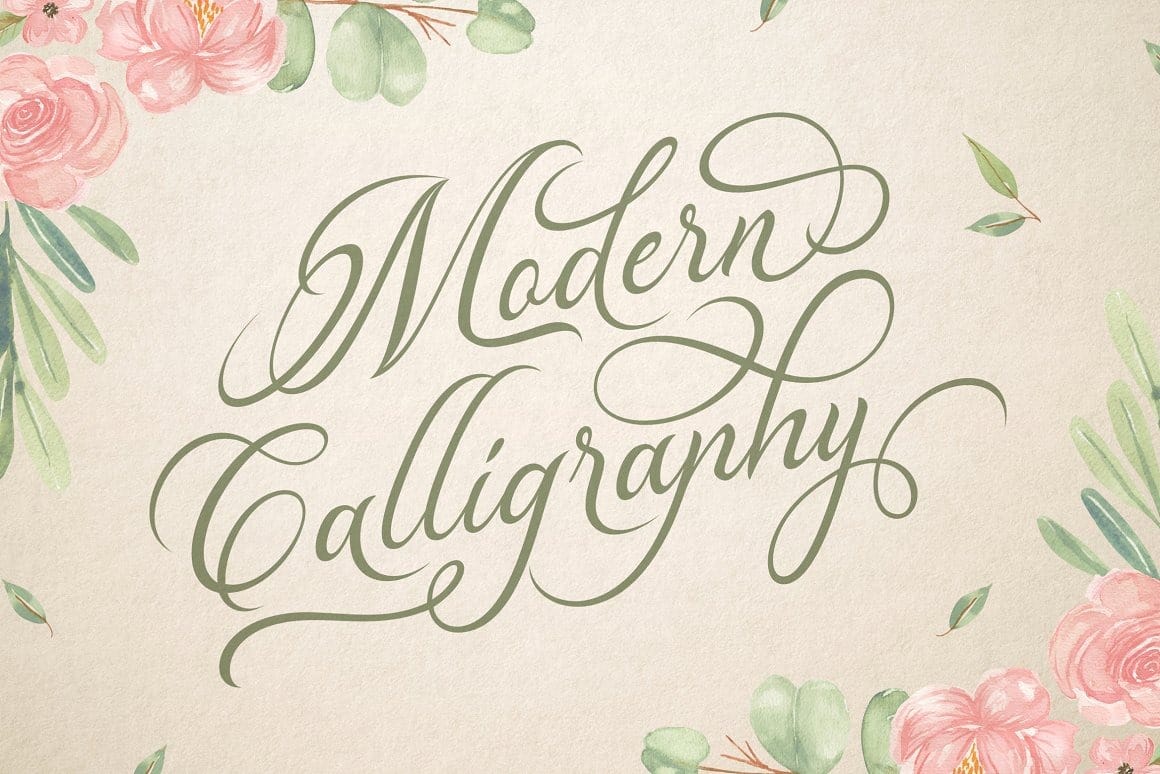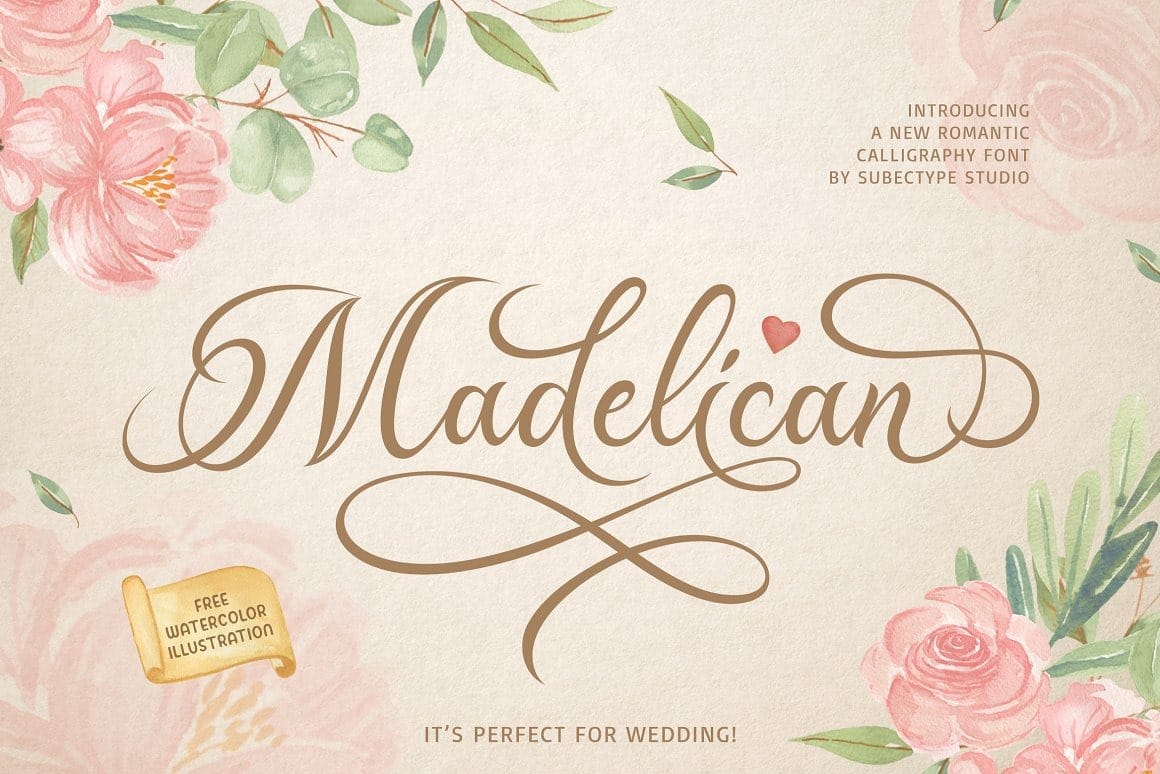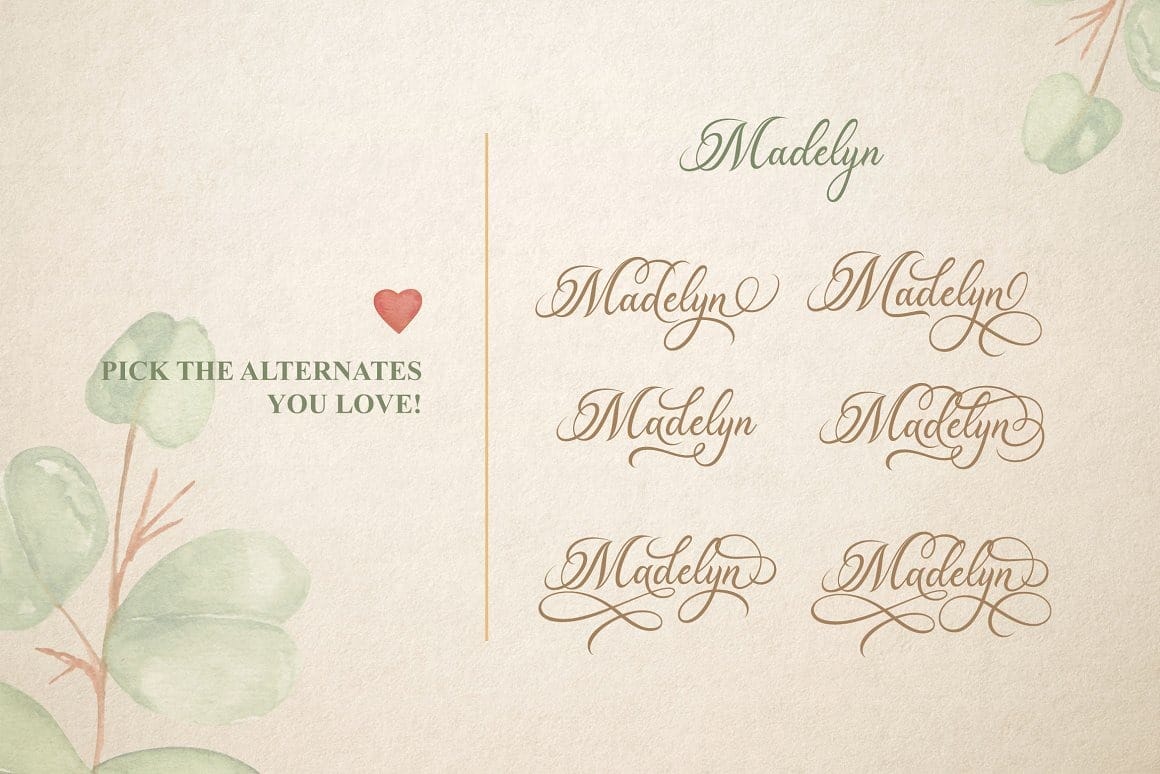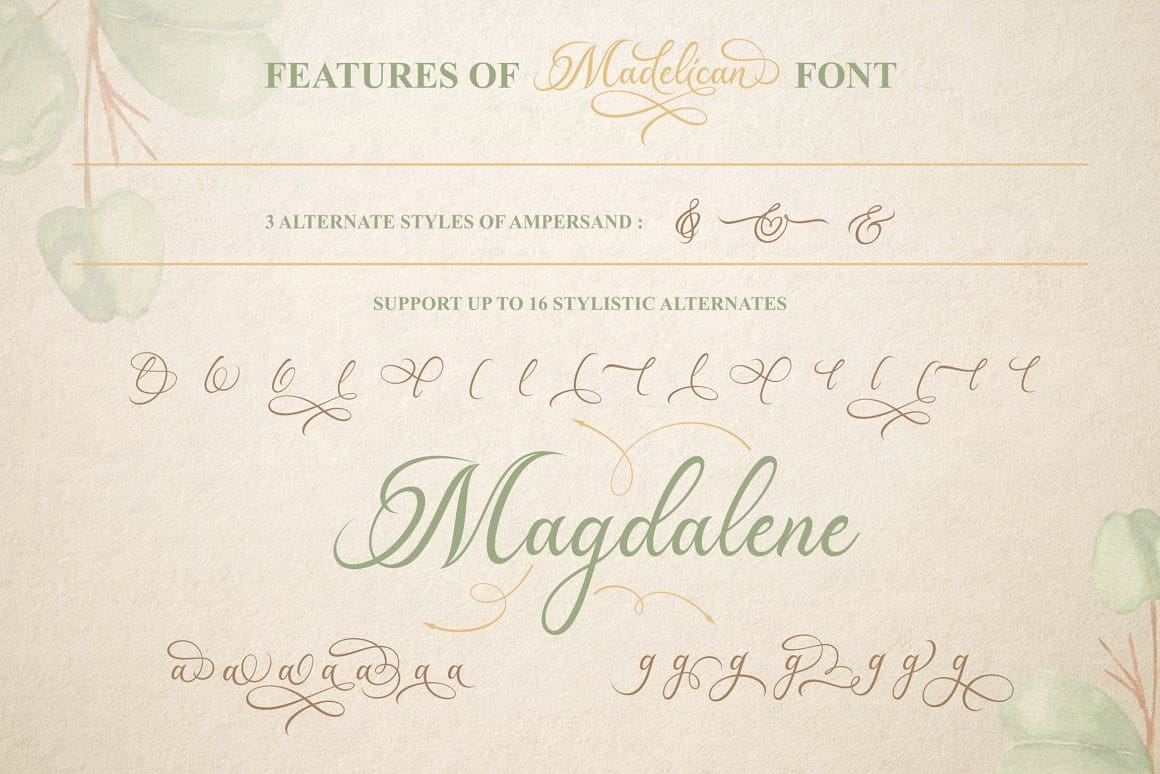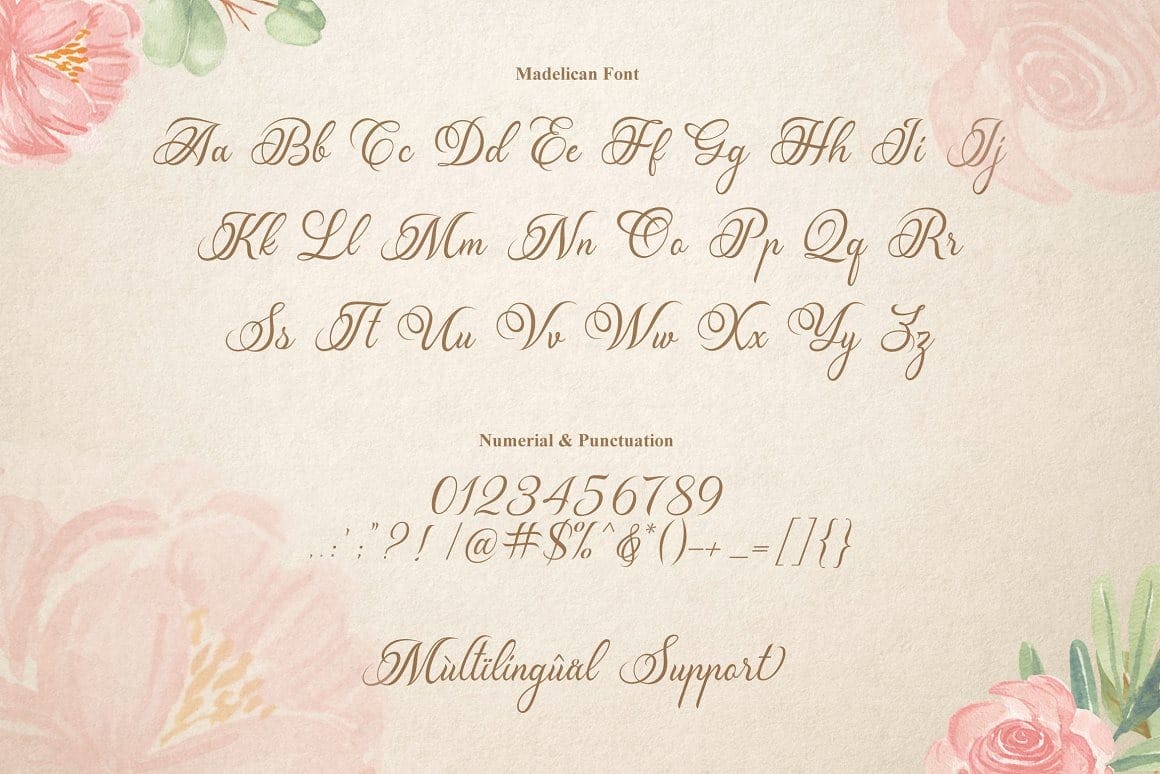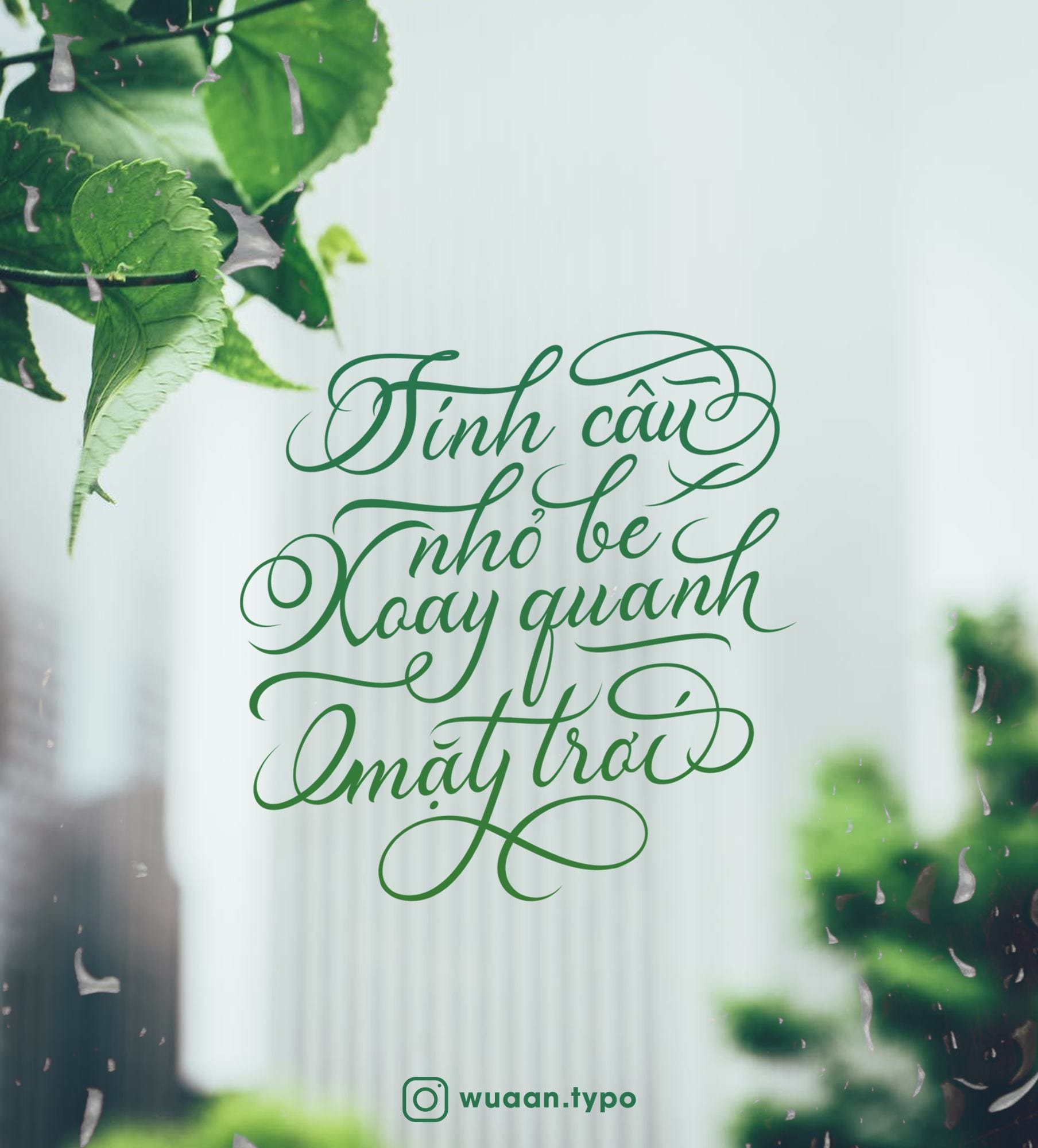
Font việt hóa Madelican Calligraphy – Font viết tay
Font Madelican Calligraphy Việt Hóa là sự kết hợp tuyệt đẹp giữa thư pháp hiện đại và cổ điển. Lấy cảm hứng từ chữ viết tay của phụ nữ Ý và những bản thảo cổ.
Font chữ này rất phù hợp cho các thiết kế như thiệp đám cưới, bìa sách, thiệp chúc mừng, logo, thương hiệu, danh thiếp và giấy chứng nhận, thậm chí cho bất kỳ công việc thiết kế nào đòi hỏi sự cổ điển, trang trọng hoặc sang trọng.
Hầu hết tất cả các chữ cái đều có nhiều chữ cái thay thế hơn những chữ cái khác, điều đó không sao cả vì hạn chế về hình dạng của các chữ cái, nó phải dễ đọc và dễ đọc.
Hỗ trợ đa ngôn ngữ và hỗ trợ lên đến 16 kiểu thay thế.